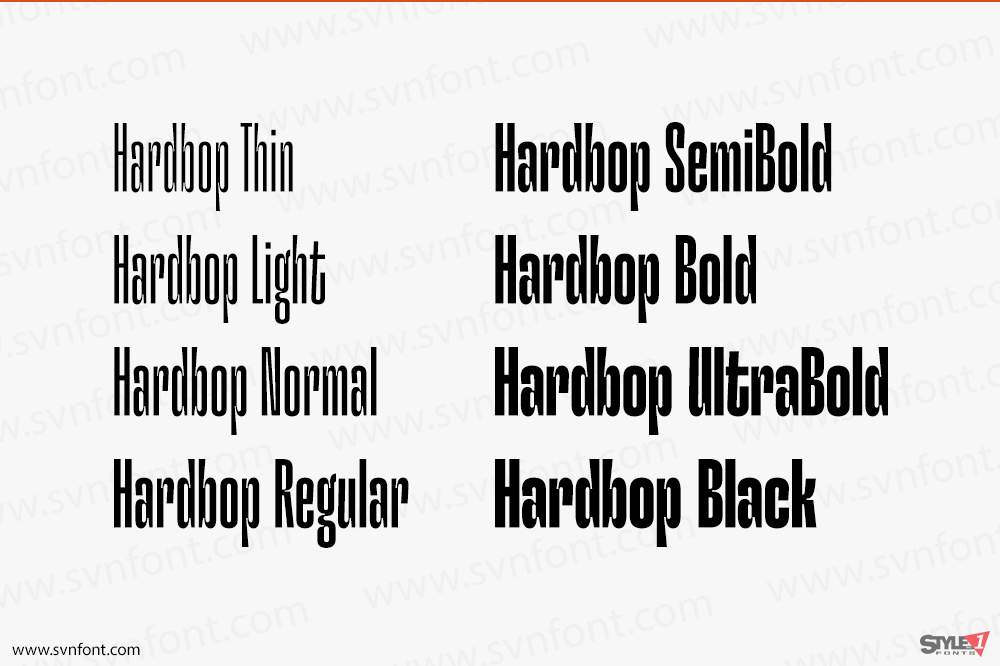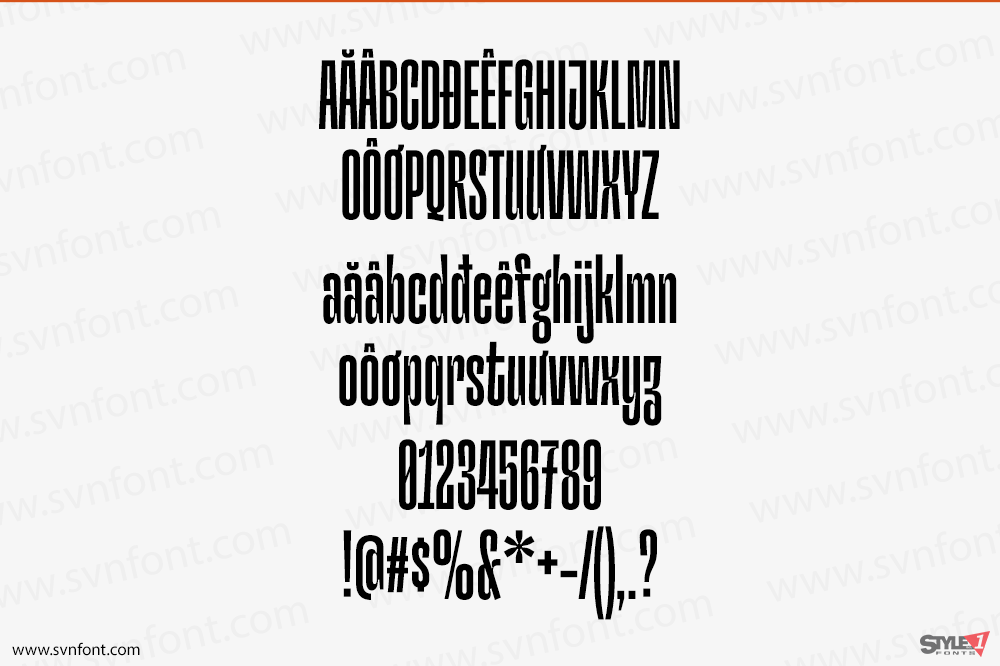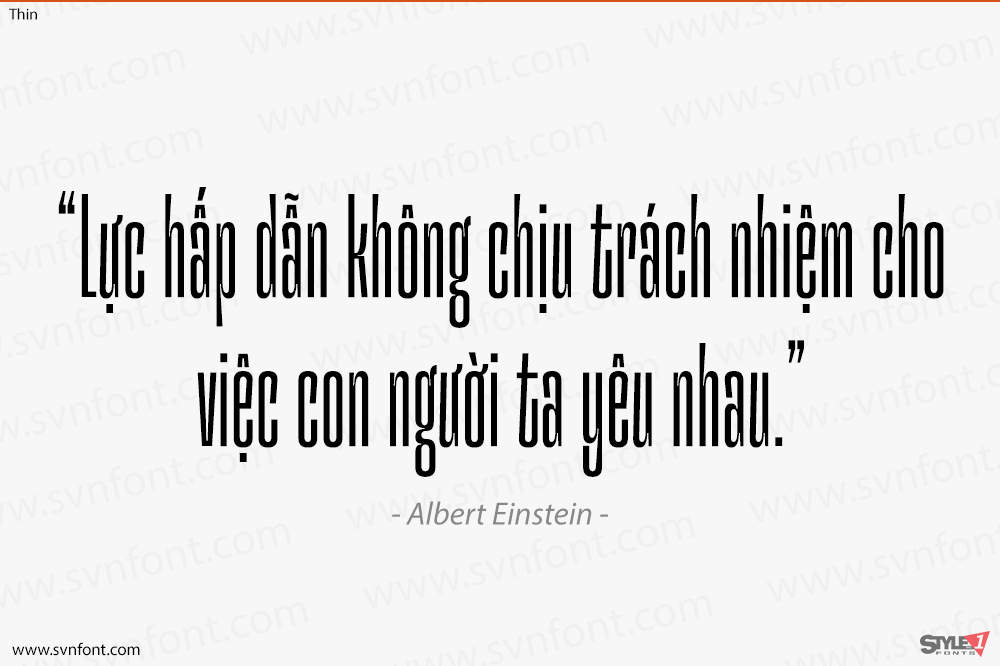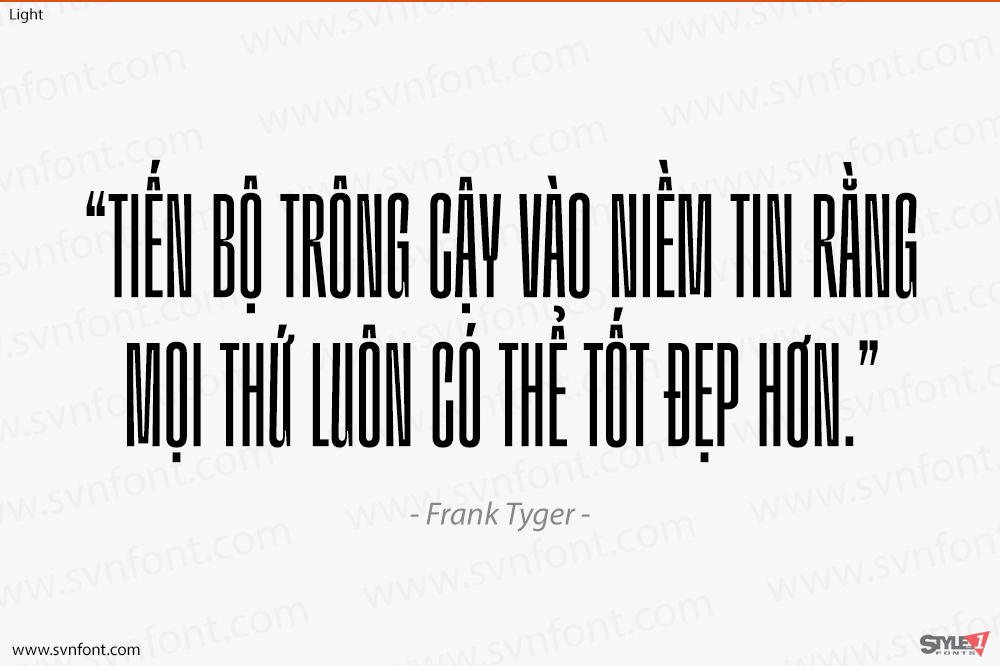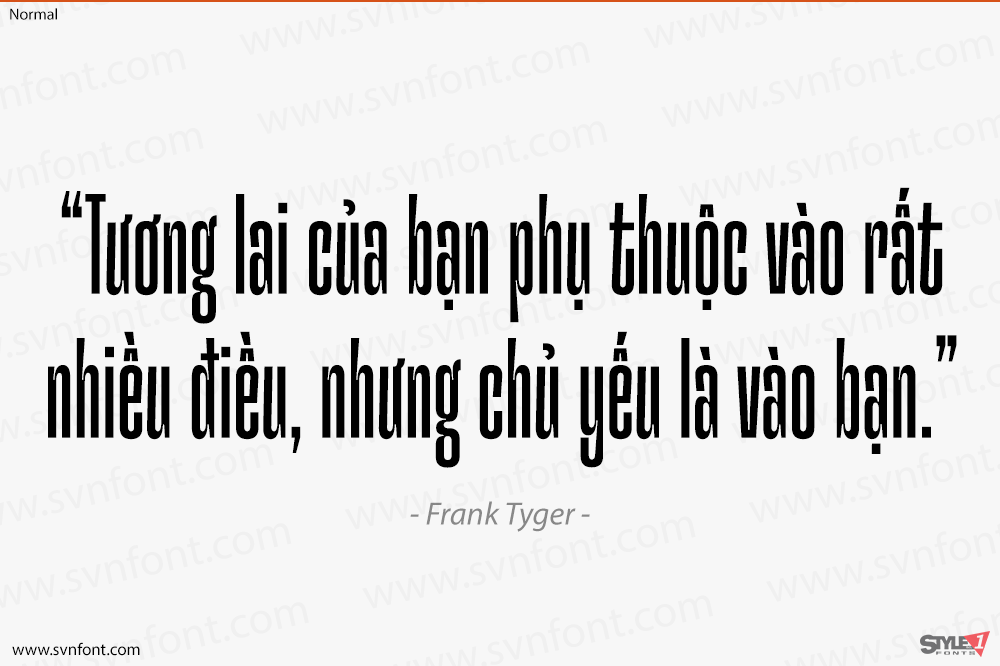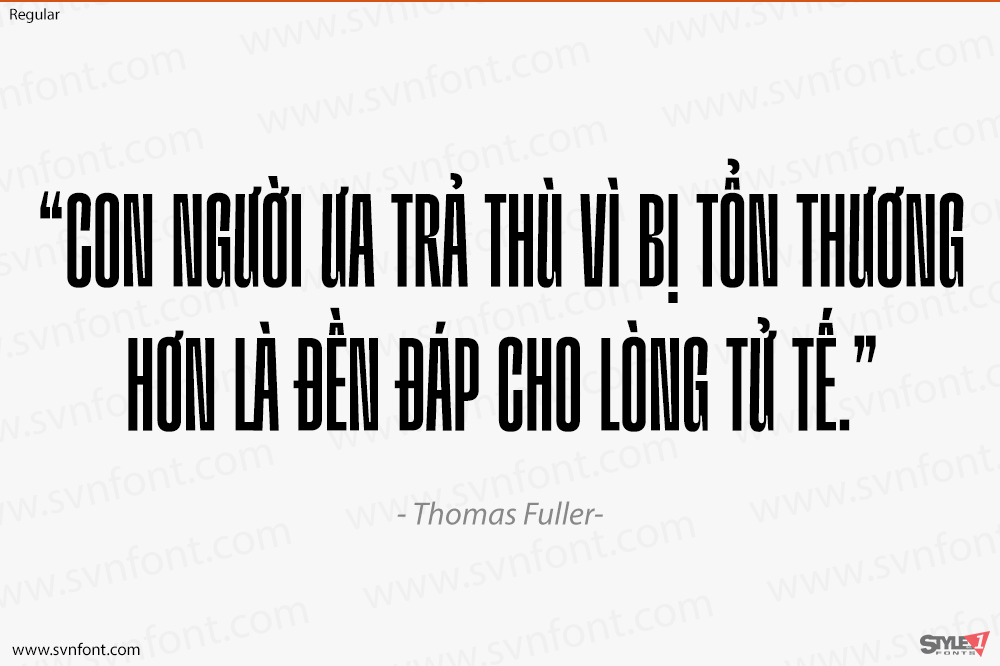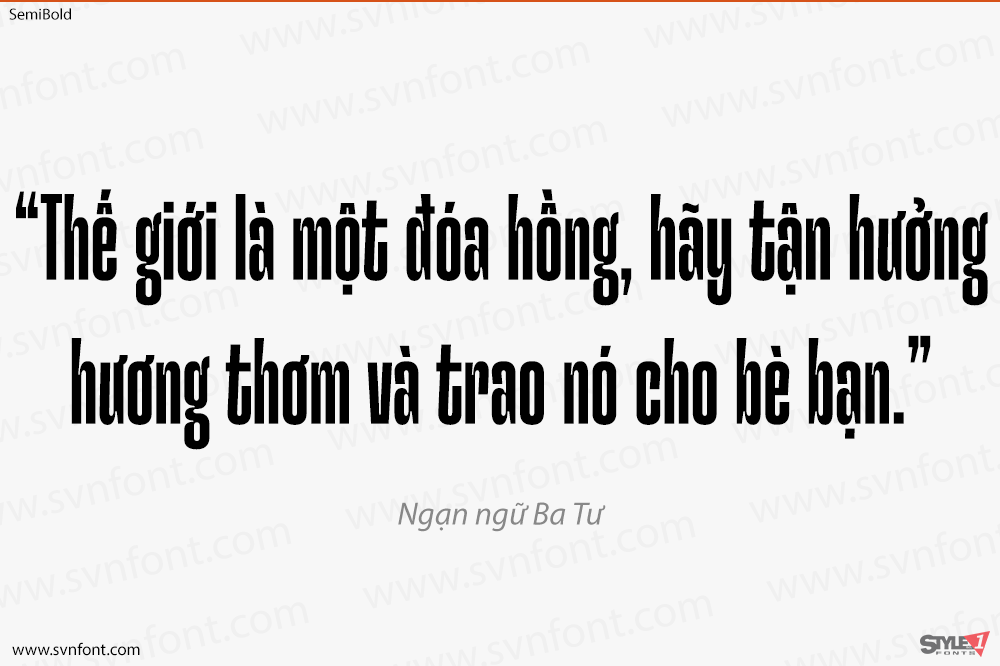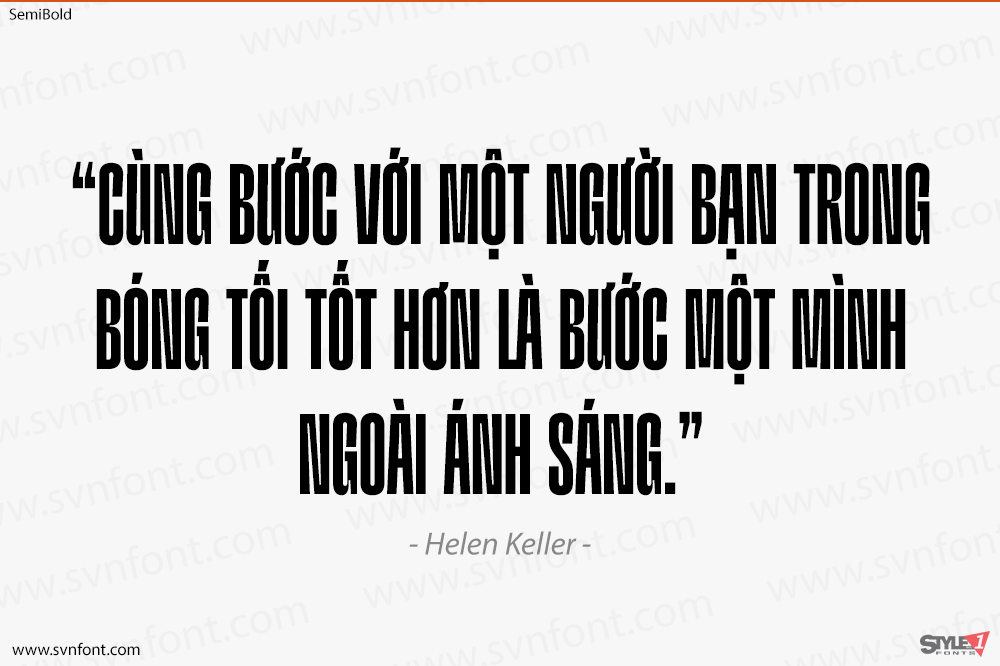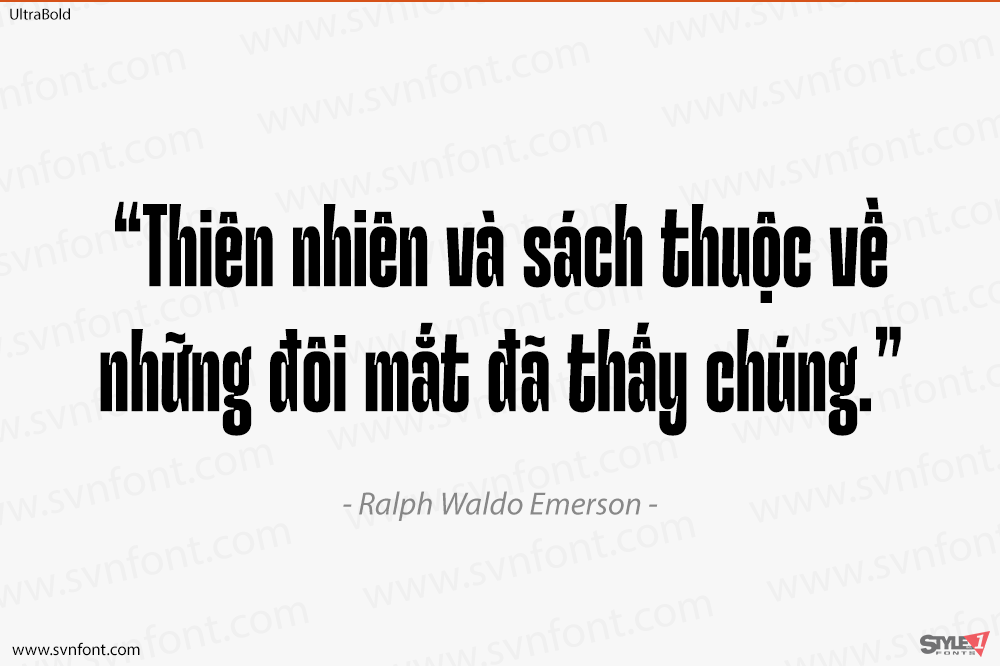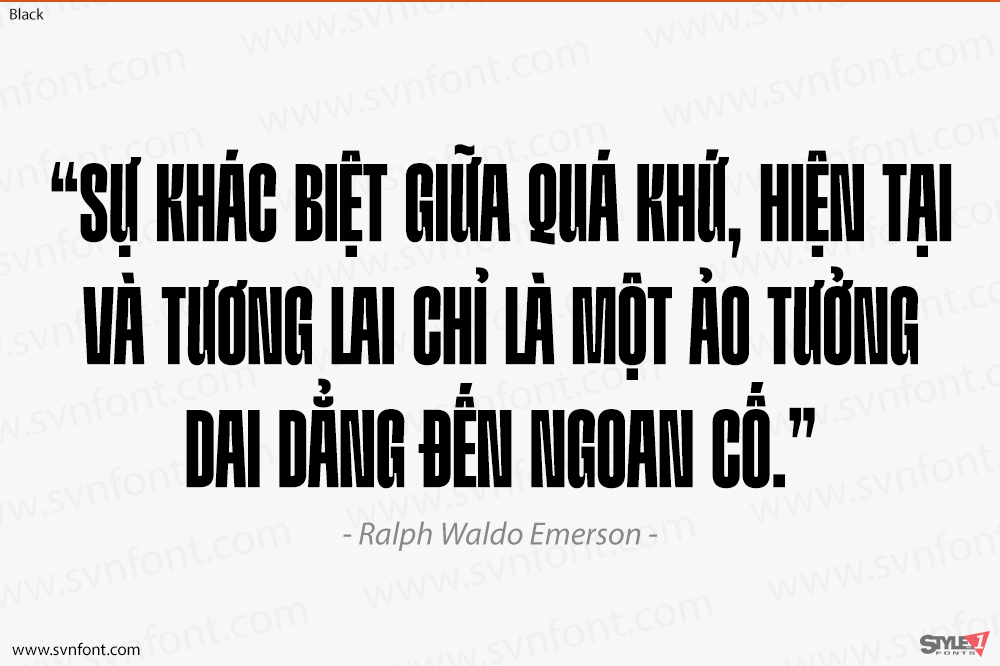
Hardbop là một hệ thống kiểu chữ lấy cảm hứng từ nhạc jazz, đặc biệt là phong cách được đặt tên theo nó: “Hardbop”. Nó cũng được lấy cảm hứng từ các tác phẩm đồ họa phong phú của Reid Miles cho các bìa đĩa Blue Notes Records vào những năm 50, bìa album jazz Nhật Bản thập niên 70 và các biển hiệu viết tay cô đọng, thô mộc.
Hardbop cũng tham chiếu các font cổ điển như Impact, Bebas, Din, Frontage và TT Trailers, đặc biệt là trong sự phóng đại của một số đặc điểm nhất định như các khoảng trống bên trong chữ (counterforms) và các điểm kết thúc.
Thiết kế Hardbop phù hợp cho các tiêu đề và không gian rộng, được thiết kế đặc biệt cho các bìa và áp phích, nơi mục đích của nó là không bị bỏ qua. Mặc dù là một họ font nhỏ, nhưng nó cho phép các khả năng chơi chữ với một bộ ký tự rộng.
Nhà thiết kế: Mauricio Astete Brito
Nhà phát hành: W Type Foundry